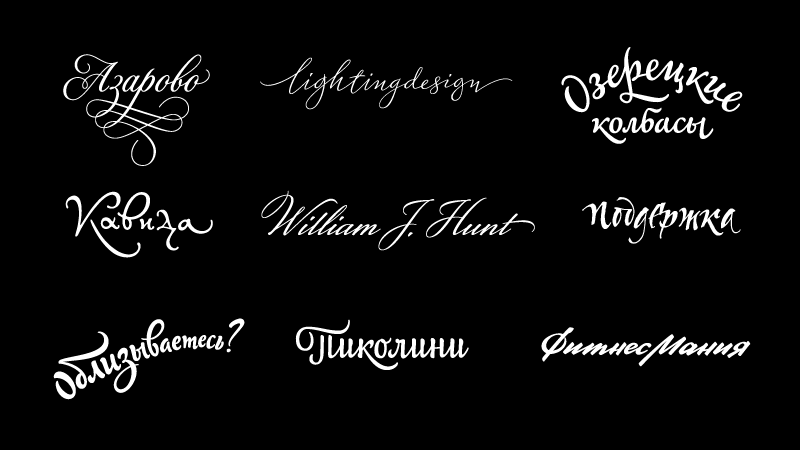
Эскизы
Сделанные в разные годы эскизы разных принятых и не принятых каллиграфических торговых марок, статусных строк и просто надписей. От русской скорописи до английского письма остроконечным пером.